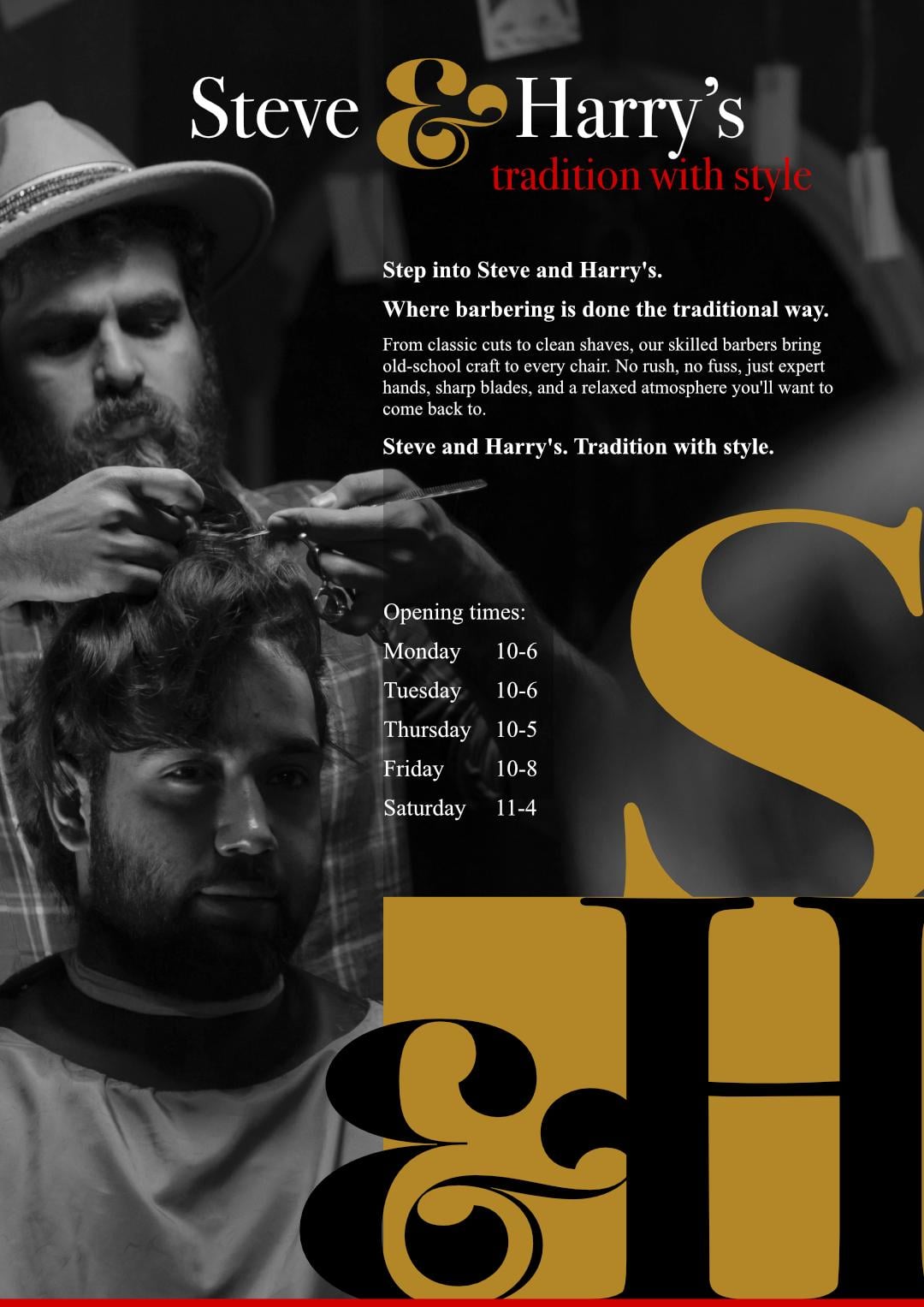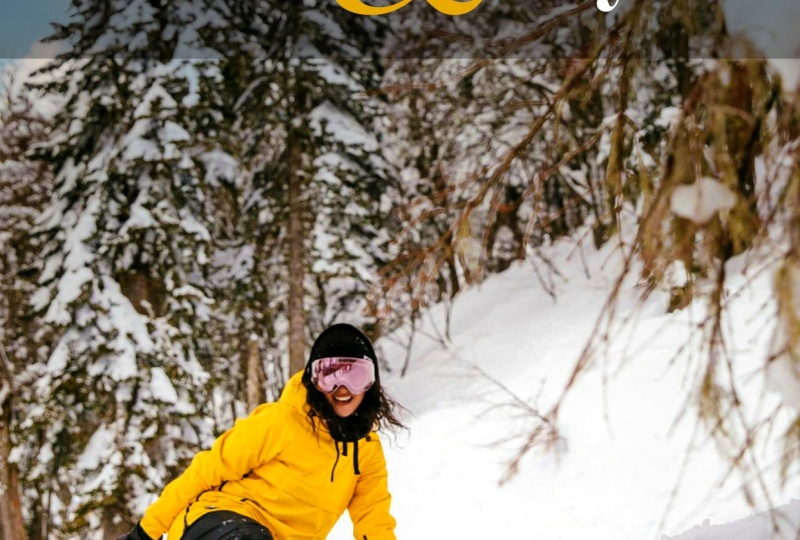
1. Diseño de texto: Introducción a este curso: El texto es una
parte tan importante de la vida cotidiana. En este curso, quiero
guiarte a través de cómo
crear
texto hermoso, asombroso y llamativo en Affinity. Este curso
te ayudará a dar vida
a tus ideas a través de
imágenes que informan, inspiran y expresan
tu visión única Empezaremos por
algunos de los conceptos básicos y trabajaremos nuestro
camino a través todos esos pequeños trozos de texto que probablemente
nunca antes habías notado. Estas son algunas de las
cosas increíbles que vas a hacer con el
texto. Echa un vistazo. Hola. Yo soy Tim. Vivo y trabajo en
¿A qué esperas? Comencemos ahora mismo, y
empecemos a crear juntos. Dos.
2. Propiedades de formato de texto: introducción: En esta sección,
vamos a estar viendo las
propiedades del texto. Entonces podría ser alejar más a tus
personajes,
alejar más las líneas, los párrafos más
separados, sangría, todo ese tipo de cosas
que necesitas saber para realmente bueno de aspecto
profesional. Empecemos.
3. Trabajar con rompes de cuadro y columna: Echemos un vistazo a trabajar con el texto dentro de los marcos. Ahora bien, lo que quiero hacer es que este pedacito de texto
fluya de este fotograma a otro aquí abajo. Y sí,
esto lo hemos hecho en el pasado. Pero lo que voy a
hacer es simplemente mostrarte nuevo muy rápido por
si te has olvidado. Tomas tu marco,
vas por aquí, y lo que estamos
buscando es una pequeña flecha. Ahí está por allá.
La pequeña flecha roja, y puedo hacer clic en
esa flecha roja, y luego puedo hacer clic en
arrastrar por aquí, y el texto fluirá de
un fotograma a otro. Además, si queremos dividir los marcos en dos
o más columnas, voy a dar click en el marco, y puedo subir aquí
para dividirlo. O también podemos hacerlo
yendo al menú Ventana, bajando al texto y encontrando el panel del marco de
texto. Y en el panel del marco de texto, podemos hacer lo mismo
y podemos
dividirlo en diferentes columnas y cambiar la cuneta
ahí también Ahora, lo que quiero hacer es mirar cómo podemos trabajar con
el texto en esos marcos. Se puede ver que tengo algo de
texto en diferentes marcos. Todos están enlazados de uno a otro, no
a la página siguiente. Y también tengo aquí, tengo algunos encabezamientos para
las distintas secciones Entonces si hacemos zoom por aquí, pueden
ver que tengo la imagen como
documento de existencia. Ese es el primer párrafo. Entonces prueba tangible de presencia es el siguiente
párrafo de aquí. El elemento humano
de la imperfección, ese es este grano es
tan impredecible, es ese, y la filosofía de intención es la última aquí dentro Ahora bien, esto está bien, pero se ve desordenado porque
tenemos el rumbo para allá, y listos queremos
que esté aquí abajo Ahora bien, una de las formas en
que podemos hacer esto, comencemos con esta
de aquí es si tuviera que hacer clic ahí
y poner una devolución, puedo obligarla a pasar
a la siguiente columna. Y lo mismo por aquí.
Voy a ir a allí, y voy a hacer unas cuantas devoluciones para forzar eso ahí.
Lo mismo con este. Y vamos a mover esa de otro lado. Y con bastante
gusto puedes hacer esto. Para conseguir que todo vaya
a las áreas apropiadas. Y ya ves que
prácticamente lo he hecho ahora. Pero acabando de hacer eso, me he dado cuenta de que
me he olvidado de tomar la prueba tangible de
presencia y moverla hacia abajo. Entonces hagámoslo ahora mismo. Entonces regresa ahí,
lo mueve hacia abajo. Y luego, por supuesto,
eso estropeó este, que tipo de puede
estropearlo, se puede ver cómo hay un poco de brecha y hay
una brecha ahí, y hay un poco de brecha en la parte superior de esa, también Entonces sí, puedes hacerlo de esta manera, pero no es lo ideal. Voy a deshacer esto
e ir todo el camino regreso allá vamos. De vuelta a donde
estábamos. Entonces, en cambio, lo que podemos hacer es en realidad
podemos obligar al
texto a pasar de un
fotograma a otro. Echemos un vistazo a
este de aquí. Entonces he puesto mi cursor justo delante de la prueba
tangible de presencia, y voy a ir al texto, y estoy buscando
algo que me
permita empujar el texto
al siguiente fotograma. Y eso es aquí abajo.
Tenemos inserto. Quiero insertar
algo que va
a empujar el texto, y
eso va a ser un descanso. Y voy a
elegir una rotura de marco, así que va a romperse y empujar eso de ahí a ese. Ahora, eso se ve bastante
bien allá porque esa está perfectamente alineada.
Pero vamos al grano. Y una vez más, el grano, voy a empujar
también, así que voy a volver de nuevo al texto. Abajo para insertar roturas, y voy a hacer una
rotura de marco en esa también, que lo empuja aquí adentro. Siguiente, igual otra vez. Vamos a ir por aquí, ir al texto, insertar descansos. Rotura de marco. Pero ahora
mira lo que pasa. Con la rotura de marco, dice, vaya al siguiente fotograma. No pasa a
la siguiente columna. Entonces apuesto a que en realidad ya puedes ver lo
que voy a hacer. Voy a regresar y hacer
eso otra vez, pero esta vez, voy a pasar
de texto, insertar,
saltos, voy a
usar un salto de columna, lo que te obligará a
pasar a la siguiente columna. Así que de nuevo por aquí, entonces
puedo usar lo mismo. En este caso, ya sea rotura de
columna o marco. Así que vamos por allá descansos. Haremos que ese
pase al siguiente fotograma. Allá, y ahora todo eso está
funcionando perfectamente. Entonces, si tengo un problema aquí y decido
hacer algunos cambios, no importará
porque estos
siempre saltarán a los lugares
apropiados. En fin, he incluido este pequeño documento para
que lo pruebes. No he vuelto
a donde era un problema. Prueba esto o
prueba el tuyo también.
4. Opciones de texto fuente, familia de fuentes, tipos de letra y contornos: Ahora, voy a ir a
buscar mi Panel de Personajes, y obviamente, tal vez lo
encuentres aquí arriba. De hecho puedo ver el mío ahí. El CH acababa de mostrarse. Pero si no puedes, ya sabes
dónde encontrarlo, menú Ventana, abajo al texto y los caracteres obviamente ahí dentro.
Vamos a sacar eso. Ahora, echemos un vistazo a
algunas de las opciones aquí dentro. Ahora bien, si has hecho el lado
vectorial de Affinity, sabrás bastantes
de estos bits y piezas, pero tengan paciencia conmigo, puede
que haya algunos bits extra que
recogerás esta vez, también. Ahora, lo primero son
las fuentes de aquí. Se puede ver esto dice A fuentes, y puedo elegir entre
diferentes subconjuntos de fuentes Así que podría ir a
mis fuentes en inglés o mis fuentes favoritas en sus fuentes recientes que
he estado usando fuentes divertidas. La lista simplemente continúa.
Voy a elegir todas las fuentes así que
las pongo todas ahí. Voy a seleccionar algunos textos. Voy a ir a este
pedacito de texto por aquí. Vamos a acercarnos un poco
a ese bit de texto. Solo usando mis atajos, Control Comando más
para acercar un poco, y voy a seleccionar
ese trozo de texto ahí haciendo clic algunas veces
con mi herramienta Texto. Entonces tenemos la
primera fuente por aquí, que en mi caso,
dice Aéreo. Ahora, cuando te encuentras con fuentes, a veces
encontrarás que en realidad se las conoce como fuentes. A veces pueden
denominarse tipos de
letra, a veces familias de
fuentes Entonces, ¿cuál es la diferencia? Bueno, si voy a
Aéreo por allá, aéreo regular 12 puntos
por ahí hay una fuente. Mientras que just aerial por
sí mismo es la familia de fuentes. La familia de fuentes incluye
regular, incluye cursiva, incluye negrita,
negrita cursiva y todos los diferentes tamaños. Solo teniendo en cuenta cuando la
gente habla de fuentes, lo
usan como término genérico realmente para incluir
las familias de fuentes. Es exactamente lo
mismo con los tipos de letra. letra son como
familias de fuentes donde se puede ir a aéreo y eso incluye todos
los diferentes estilos
y tamaños. Si solo quieres
llamarlos fuentes, bueno, solo las personas más tensas
se entusiasmarán con eso De todas formas, me voy a mudar
un poco hacia abajo por aquí. Voy a ir
al tamaño porque cuando tienes un poco de texto y tienes
el tamaño ahí, el tamaño viene en puntos. Ahora bien, en lo que respecta
a los puntos, ¿qué tan grandes son los puntos? Bueno, en una computadora, hay 72 puntos en una pulgada. Entonces, si seleccioné este título por aquí y pongo
72 puntos ahí dentro, solo
vamos a ir a 72. Ese sería 1 "
texto alto en mi documento. Pero, ¿y si no te
gusta usar puntos ahí dentro? Y pensaste,
Bueno, ¿sabes qué? Realmente quiero que ese pedacito de texto sea exactamente de
8 milímetros. Bueno, puedes
teclearlo directamente, así puedo entrar aquí y
puedo escribir ocho MM, presionar Enter, y
lo convertirá en tamaños de puntos
para mí, también. Sólo un poco
de un lado aquí, sí
dije que hay
72 puntos en una computadora, y eso es porque la
tipografía tradicional , en realidad es 72.27 Así que por si acaso
alguien te detenga y te diga:
Bueno, en realidad, hay 72.27 Ya sabes de lo que están
hablando. Eso es tradicional. Estaba
en una computadora apenas 72. Ahora, bajemos un
poco por aquí, y tenemos los botones
habituales que ves en todo
tipo de cosas. Entonces por aquí,
tenemos subrayado. Tenemos por aquí, subrayados
dobles ahí dentro Tienes pasos de strike throughs y tienes doble
strike throughs, y luego puedes
eliminarlos ahí dentro. También puedes, si lo deseas, entrar aquí y cambiar el color, así podría hacer un subrayado
rojo
allá con este pequeño
color de aquí Voy a simplemente
deshacerme del subrayado dando clic de nuevo en la U del
lado izquierdo Ahora bien, ¿qué es este de
aquí abajo que dice ninguno? Bueno, voy a seleccionar
este pedacito de texto por aquí. Podría hacerlo un
poco más grande. Entonces 22 puntos, creo que voy
a ir 30 puntos ahí, solo para que sea más fácil que
veas . Voy a ir por aquí. Haga clic en eso, elija un color. Vamos con algo
bastante brillante y vibrante y aumentemos el tamaño y verás
exactamente lo que hace. Es la línea alrededor del
exterior del texto. Podría hacer eso y
poner la línea alrededor la parte exterior del
texto ahí dentro,
y entonces en realidad podría
quitar el centro de mi texto. Puedo ir al
color de mi texto y luego decir ninguno, y eso solo dejará
texto abierto con solo el contorno. Verás si lo muevo y vamos a pasarlo por encima de la foto. Voy a
traerlo al frente, así que voy a subir
por aquí a mis capas, y voy a ir
a rango y decir,
llevar al frente, y se
puede ver cómo ese texto es realmente
transparente en el medio. Así que sólo voy
a deshacer eso para que
lo veas otra vez por allá. Entonces, si tienes algún texto, puedes ponerle una línea alrededor. Vamos a ir a las decoraciones
de aquí una vez más, y entonces puedo elegir
un color ahí dentro. Y luego puedo ir a la talla, y puedo cambiar el tamaño en eso para la línea
alrededor del exterior. Si quiero deshacerme del color de
relleno del texto, puedes subir aquí, el
segundo a lo largo, así que es, perdón, el primero
largo, alguien a la izquierda. Cambia el color de la fuente a ninguno.
Esa es una pequeña línea roja. Y ahora eso está bien, texto
invisible, pero la línea alrededor del exterior es visible. Voy a volver
otra vez por aquí al tamaño de eso, y pueden ver cómo puedo ajustar el tamaño con el texto
invisible ahí dentro. También puedo ir y usar
cualquiera de estos otros estilos, así podría ir y tenerlo como
una línea punteada por allá. Ahora bien, la otra cosa que podemos
hacer es que podemos alinear esa línea, y podemos
optar por tenerla en la
propia línea por dentro
o por fuera. Tú eliges cuál prefieres. Vaya un poco con eso y particularmente con
las decoraciones, si nunca ha probado estas
líneas alrededor del exterior
del texto o texto transparente
con la línea. Tener una oportunidad.
5. Posición y transformación del personaje: Yo vayamos a posicionar
y transformarme. Si no puedes ver estas opciones, simplemente haz clic en la pequeña flecha de
ahí para abrirla. Ahora bien, el primero al
que llegamos aquí es algo
llamado kerning cambia las
distancias entre caracteres
individuales.
Déjame mostrarte. Voy a ir por aquí
y voy a acercarme un poco por allá a la IA,
donde dice IA generativa, y voy a hacer click para que mi herramienta de texto esté sentada
entre la A y la I. Ahora lo que puedo hacer es que pueda ir junto a mi kerning
y puedo o bien aumentar esa distancia que
ves toma un poco Hay
ajustes muy, muy finos por allá, o podría disminuir
esa distancia ahí dentro. Pasemos a una
cifra menos para que podamos empujarlo muy
cerca si es necesario. Ahora bien, para la mayoría de los textos, no
necesitas
cambiar
mucho el enlatado a menos que estés tratando de
hacer algún tipo de efecto Pero si descargas
alguna fuente interesante, que tal vez no esté tan bien creada en primer
lugar o bien diseñada, encuentres que el timón
no se ve bien y es posible que tengas que
entrar y
curarlo manualmente tú mismo Muchos diseñadores pasan horas
y horas simplemente ordenando la conning en su texto
para que sea así Y es bastante divertido
una vez que te metes en ello. Pero si solo quieres
poner algún texto muy rápido y tienes
un tipo de letra bien diseñado, como Ariel, por ejemplo, no
necesitas hacerlo
cono a menos que
quieras hacer un efecto específico Ahora, sigamos adelante. Si voy aquí abajo a
este VNA por aquí. Ahora, para este VNA, necesitamos seleccionar las palabras Seleccionaré la palabra
en lugar de
simplemente poner el cursor
entre los dos caracteres. Y por aquí, puedo aumentar las distancias entre esos
personajes o disminuirlos. Ya ves que puedo ir a negativo o puedo ir positivo allá. Y voy a dar
click en ese
desplegable y volver a cero. Ahora bien, ten cuidado con
este porque si lo
pones en un texto normal como este, podrías terminar
siendo tu texto bastante difícil de leer si está demasiado separado o
demasiado cerca. Un poquito de
esto puede ayudar si, por ejemplo,
quieres empujar un trozo
de texto a la siguiente línea, o si solo tienes una palabra sentada
sola y quieres que esa palabra
vuelva al resto
del párrafo, tal vez
quieras seleccionar todo
el párrafo y ajustarlo
muy, muy ligeramente. Pero no te vayas
por encima con eso. Ahora bien, hay
momentos en los que quizás quieras
poner mucho kerning, pero eso volvería a
ser para más efecto Entonces digamos, por ejemplo, con este bit por aquí,
solo quiero la palabra existencia. Entonces voy a quitar este
pedacito de texto por ahí. Yo sólo voy a poner una E ahí. Y me gustaría hacer esto más cinematográfico así que
es más importante Voy a bajar por
aquí y voy a aumentar eso para conseguir más
distancias entre ellos. Así que eso le da una
sensación más cinematográfica. Encontrarás que la
gente suele usar esto cuando se trata de encabezados. Tu texto grande se ve muy, realmente cinematográfico, se ve
muy, muy bien así Pero para el texto corporal normal, no lo
usaría a menos que esté buscando mover algo
de una línea a la siguiente. Echemos un vistazo a ajustar las distancias
entre las líneas. Esto se conoce como líder. Entonces, si voy aquí abajo, verás que
puedo o aumentar las distancias o
disminuir las distancias. Si no estás seguro de lo que debes usar, simplemente haz clic en esto. Se despliega y elige auto. Y ese será
el líder normal para ese trozo de
texto en particular o esa fuente en particular. Ahora, tenemos algunas
otras opciones aquí. Por ejemplo,
puedes tomar tu texto, y puedes obligarlo
a que se ponga todo en cursiva. Puedes moverte hacia abajo, y puedes cambiar el tamaño del texto y
hacerlo tan ancho Puedes hacerlo alto. También. Y por último, aquí abajo, entonces
podemos entrar y podemos usar superíndice o subíndice, y eso va a tomar algo
y hacerlo pequeño y subir Entonces, por ejemplo, después de la
palabra fotografía aquí, tengo TM marca registrada, y puedo seleccionar eso y luego
puedo ir y hacer
ese superíndice, que lo hace un
poco así Si uso subíndice, hará
lo contrario y lo
hará pequeño y bajará Elige ninguno para
volver a tu original. Tener un poco de un ir con eso. Y en el siguiente video, lo
estoy llamando por la
madriguera del conejo porque voy a entrar en muchos más
detalles aquí. No necesitas todos los detalles. Si quieres saltarte
eso y pasar
al siguiente video,
eso está absolutamente bien. Pero si realmente te
interesa más tipografía, entonces mira la siguiente
6. Al fondo de la aguja de conejo: posición y transformación: Entonces comencemos a
bajar por la madriguera del conejo.
Agárrate a un sombrero. Lo que voy a hacer
es echar un vistazo a algunas más de las
opciones que
no son tan normales como las habituales a las
que uno está acostumbrado. Entonces comencemos con este de aquí llamado
el cambio de línea de base. Verás, tu texto se asienta
sobre una línea de base invisible. Y lo que podemos hacer es ir a
lo largo del texto y
podemos seleccionar caracteres, palabras, o párrafos enteros. Y podemos cambiarlos, así puedo moverlos hacia arriba
o puedo moverlos hacia abajo. Ahora bien, ¿por qué
querrías hacer esto? Bueno, digamos que teníamos
algo así como una fracción. Ahora, voy a hacer
una fracción de 1/34. Así podría tomar el uno, y podría hacerlo subíndice, y podría tomar el 34 No, lo siento, superíndice. Y puedo tomar el 34, y puedo hacerlo
subíndice por allá Pero se puede ver que el
34 es demasiado bajo, así que puedo subir aquí
y puedo simplemente
empujarlo hacia arriba usando el
cambio de línea de base ahí dentro. También se puede utilizar
para todo tipo de efectos para texto así como para
poder moverlo. Ahora,
aquí hay una pequeña opción llamada no break. Si voy y decido que estas ciertas palabras
que quiero
mantener juntas como demasiado limpias, por
ejemplo, no quiero que sea división de palabras y una esté en una línea y una
en la Lo que puedo hacer es no ponerme descanso. Pero antes de hacer eso,
déjame
mostrarte lo que pasaría por aquí. Si empujo esto
más cerca, ahí vamos. Se puede ver que
tenemos dos limpios en dos líneas ahí dentro. Ahora,
déjeme hacerlo otra vez. Voy a seleccionar dos y limpiar, y voy a poner en
un no break por allá. Ahora, intentemos eso otra vez. Empuja esto demasiado limpio, y ahí vamos. Se puede ver que es simplemente empujado
demasiado limpio en la nueva línea. No ha puesto dos en uno
y limpio en el otro. Así que ningún descanso solo
te impide dividir palabras. Una vez más, pruébalo un
poco con eso, pruébalo. Esa es útil, pero el cambio de línea de base
es muy, muy útil.
7. Por el abismo del conejo: lenguaje, alineación óptica, puntuación colgante: Voy a ir
al idioma y
abrirlo muy rápido
porque aquí dentro, tenemos el idioma
para la ortografía, y no es solo el inglés. Se puede ver que hay variaciones
del inglés ahí dentro, y la otra que me parece bastante importante es la sílabe,
donde vas
a tener la sigrafía
automáticamente encendida
o ninguna automáticamente encendida
o Cerremos ese y
pasemos a la alineación óptica. Ahora, cuando eliges la alineación
óptica, obtienes esta pequeña mesa
de cosas realmente
rara aquí abajo. Entonces déjame mostrarte
cómo funciona esto. Lo que voy a hacer es que
sólo voy a volver a mi último texto aquí arriba. Y como pueden ver, aquí hay algunas cosas como
la palabra alucinar Y el alucinato tiene comas
invertidas alrededor de él. Así que voy a echar un vistazo
aquí al tipo que va a ser de tipo de
letra en lugar de ninguno. Voy a ir
aquí a los personajes, y se puede ver así es como controla a los diferentes
personajes y
lo que hace desde el movimiento de la izquierda y la derecha para
ciertos personajes. Aquí hay todo tipo de
diferentes. Voy a desplazarme un poco hacia abajo. Pero sólo vamos a
mirar las comas invertidas, y luego puedes como que descubras
cómo funciona
el resto de ellas tú mismo Déjame comenzar con alucinar. Y si hago un retorno por aquí, he puesto mi cursor antes las comas invertidas y
he hecho una devolución, puede ver que las dos comas
invertidas están
sentadas afuera, así que el texto está
alineado perfectamente Y eso es porque aquí
en la alineación óptica, tenemos el
encendido para esos personajes. Si solo elijo ninguno ahí, solo selecciónelo de nuevo y
elija ninguno por ahí. Se puede ver que simplemente vuelve
dentro del propio cuadro de texto. Puedes decidir lo
que quieres hacer. Voy a seleccionar eso
otra vez y por aquí, voy a elegir fuente y la
va a empujar afuera. Ahora bien, aquí es donde
puedes controlarlo tú mismo. Puedes entrar entonces puedes decir,
Bueno, en realidad, ¿sabes qué? En realidad quiero aumentar
eso un poco, así que sale justo ahí afuera
o disminuirlo un poco. Entonces puedes hacerlo
con la alineación
izquierda o derecha. Entonces como dije antes, ahí abajo
tenemos todo tipo
de opciones para
los personajes. Si no estás seguro de lo
que quieres, solo tienes que ir a ninguno ahí dentro
volverá al texto normal. Entonces, echa un vistazo
al lenguaje y a las
alineaciones ópticas que hay ahí dentro. Estoy tratando de no caer demasiado por la
madriguera del conejo con esto. Puedes meterlo más
en esos si lo deseas, pero solo quiero
darte un
bosquejo de cómo funcionan.
8. En el abismo del conejo: ligaduras tipográficas: Ahora, bajo tipografía,
una vez más, si no la puedes ver, da
clic en la pequeña
flecha que hay por Tenemos a este
pequeño FI aquí. Esto se llama ligadura. Ahora, las ligaduras, verás van a funcionar
a veces y no a otras. Entonces quiero mostrarles
qué es, qué hace, y por qué aparece y
a veces no ve, tengo un trozo
de texto por aquí, y este texto es aéreo. Y si enciendo y apago la
ligadura, puedes ver que todo lo que está
haciendo es
mover ligeramente la F y la
I más juntas Así. Pero donde las
ligaduras realmente se hacen propias es cuando
estás usando un tipo de letra, que tiene serifs, esos son los pequeños
rizos en los extremos Entonces, por ejemplo, si bajé aquí y elegí
algo con serifs, echemos un
vistazo y veamos si podemos encontrar algo aquí abajo Sólo voy a
correr todo el camino hacia abajo y encontrar Times New Roman, porque ese es un tipo de letra
serf muy tradicional Así que los tiempos New Roman por allá. Entonces, apaguemos las ligaduras. Y lo que encuentras
es que la F y la I sin ligaduras
están muy juntas Y tienes el
punto en la I y
el poco rizado en la F. Entonces lo que
hace una liicatura es que toma esos dos personajes y
los convierte en uno así Entonces sigue siendo legible como FI, pero se ve mucho mejor. También significa que si
estás haciendo impresión, a veces si no tienes
una liicatura así, estando
esos dos juntos, la tinta puede
correr entre ellos y crear una gran
gota de tinta ahí dentro, que se ve muy
pobre desde Entonces eso es todo lo que hacen las liicaturas. Toma ciertos
personajes y los
convierte en un solo personaje que en
realidad sigue siendo dos
personajes así. Pruébalo con
diferentes tipos de caras, y verás las diferencias. Como dije, realmente solo funciona correctamente en aquellos que tienen un poco rizado en
la parte superior, las serifs Al mirar algunas más de
estas opciones por aquí, tenemos todas las capitales. Ahí tenemos
capitales pequeños. Entonces, si la F, por ejemplo, en Find era una mayúscula
y yo lo hice,
verás que tendría
un gran capital y luego las
capitales más pequeñas ahí abajo Estos dos de aquí son
superíndice y subíndice, y este te permite
convertir las cosas en fracciones Ahora bien, esto
depende de la fuente que realmente
estés usando. Voy a ir a buscar
un poco de texto aquí. Este texto es aéreo y
voy a ir a poner aquí una fracción. Voy a hacer una barra cuatro. Voy a seleccionarlo y
luego presionar ese pequeño botón y lo convertirá en una fracción de aspecto
agradable para mí. Déjame deshacer eso.
Pero si hice uno, sé, 32, una vez más, selecciona eso
y da click en eso. No tiene un solo
carácter para reemplazar eso, así que tienes que hacer
algunos de esos manualmente. De igual manera, cosas como S T
y así primero, segundo, ND, RD para tercero, si tu
fuente lo soporta, puedes reemplazarlos muy rápidamente con esos
pequeños botones ahí dentro. De lo contrario, todo lo que
necesitas hacer es seleccionar los caracteres
que quieras y usar
superíndice y subíndice y
luego tal vez moverlos hacia arriba y hacia abajo usando el
cambio de línea de base para que las cosas Tengan un poco
de oportunidad con eso, particularmente entendiendo
cuáles son las ligaduras, y luego saldremos de la madriguera
del conejo
9. Opciones de párrafos: alineación: Et, echa un vistazo a
las opciones de párrafo. Ahora, pongo algo de texto en
otra página aquí solo para que sea fácil para ti verlo sin todas las distracciones,
fotos, etcétera Y voy a ir a
buscar mi panel de párrafos. Voy a cerrar el panel de
personajes. Ahora, obviamente,
si no lo encuentras, ya
sabes a dónde ir,
menú de ventana, texto, etcétera Entonces, antes que nada, las pequeñas
opciones a lo largo de la parte superior. Ahora, sé que estos parecen obvios, pero hay una o dos cosas
que quiero mencionar. Solo seleccionemos
todo este texto, y tengo la
línea izquierda o la línea central, línea
derecha por ahí. Ahora tienen perfecto sentido. Estos siguientes de aquí, aquí es donde se alinea a
ambos lados del marco de texto, pero la última línea está
alineada a la izquierda Esa de ahí, la
última línea está alineada a la derecha y
esta a la pena, a la mitad y esta
a la derecha. Pero se puede ver porque es que los titulares son solo
una línea por sí mismos, los alinea también Entonces, si quisieras usar esos, me aseguraría de que
no lo hiciste en el titular. Por supuesto, esto es
algo que puedes configurar y veremos más adelante con estilos. Así que allá,
solo podría hacer uno de esos. Ahí. Ahora, esos son esos tres. Este de aquí se
trata de conseguir que
el texto se siente en todas las líneas y
llene todas las líneas, lo que podría verse muy
bien desde la distancia. Pero se puede ver lo que
se hace con esta última línea es que simplemente se ha separado
las palabras, y hace que parezca
bastante ilegible, todo si lo haces sobre
todo así Mira lo horrible que
se ve en este momento. Es decir, esta de aquí se
basa en una reacción fotoquímica. Incluso en el párrafo, se
ve muy, muy mal. Pero, ya sabes, si
quieres, ve a por ello. Ahora, vamos a echar un vistazo a éste de aquí o a
estos dos, ¿diría? Porque esto es
ligeramente diferente. Se puede ver que tenemos una línea a la izquierda y una línea
a la derecha ahí. Pero estos tienen el mismo aspecto. Esa parece la
línea a la derecha. A lo largo de entonces, si hago clic en él. Bueno, funciona exactamente
igual que este de ahí dentro. Entonces, ¿cuál es la diferencia
entre estos dos? Bueno, tiene que ver con tener
un pliego de página doble. Si tienes una doble
página extendida como esta, si voy a esta opción de escritura
alineada, puedo mover esto, solo vamos obtener la herramienta de movimiento y
moverla a través de este sitio, y sigue siendo
escritura alineada. Pero digamos que siempre
quise que mi texto estuviera alineado
al centro de la página. Bueno, si elijo este de
aquí, vamos una vez más, sólo
vamos a ir y
seleccionar todo el texto, y voy a elegir
este de aquí, que dice alineado
hacia la columna vertebral. Ahora mira lo que pasa. Si tomo este pedacito de texto y lo
pongo de ese lado, entonces
se alinea de la manera opuesta Por lo que automáticamente simplemente salta y
se alinea con la columna vertebral Entonces tenemos este
de aquí, que se alinea
lejos de la columna vertebral Entonces, una vez más, puedes
ver cómo se mueve eso, dependiendo de si
estás en una página del lado izquierdo o derecho. En fin, ¿tienes un
poco de juego con esos? Es interesante
saber de esos. Podrías o quizás
no los necesites nunca, pero es bueno
saberlo. Pruébalos.
10. Espacio de párrafos e indentación: Echemos un vistazo a algunos
de estos los importantes. Entonces, antes que nada, iniciando aquí arriba, podemos sangrar. Entonces voy a ir
a lo largo de este párrafo aquí y puedo sangrarlo
desde el lado izquierdo, y también puedo sangrarlo
desde el lado derecho Voy a ir al siguiente
párrafo, éste de aquí. Sólo lo estoy resaltando, y debajo de eso en el lado
izquierdo aquí, podemos sangrar la
primera línea si queremos Eso es bastante útil.
Si vas a estar haciendo en lugar de hacer espacios
normales entre
tus párrafos, solo
puedes usar esto para
denotar un nuevo párrafo Ahora, echemos un
vistazo a estos dos de aquí, donde tenemos espacio
antes y espacio después. Ahora bien, lo que voy a hacer
aquí es que voy a seleccionar este pedacito de
texto por allá, seleccionar todo para
que lo veas fácilmente entre ese encabezado
y ese rumbo de ahí. Entonces puedo seguir adelante y puedo aumentar el espacio después de eso. Ahora, también puedo aumentar el
espacio antes de allá. Podrías, por cierto,
si se pone a cero, quizás
tengas que
ir un poco primero antes de que realmente
empiece a moverlo. Así. Por lo que estos dos permiten más espacio antes o
después de los párrafos. Por cierto, si se trataba dos párrafos en ella funciona también
entre párrafos, no
se trata sólo de entre titulares y el otro y
los propios párrafos. Como pueden ver, sólo puedo
mover esos alrededor así. Entonces, una vez más, prueba aquí las opciones
importantes, que es la alineación por ahí o la sangría, ¿debo Y luego también, esto
es muy importante, el espaciamiento entre
los párrafos.
11. Control de la pestaña de párrafos: Tengo algunas pestañas aquí. Así que lo que he hecho es que
he pulsado la tecla de tabulación y he puesto un
número ahí dentro, luego tabulación de nuevo otro número, número tabulación número de tabulación. Y voy a seleccionar a
los de aquí. Y vamos a bajar
a las paradas de tabulación. Ahora bien, si no los puedes ver, es simplemente hacer clic en el pequeño
menú desplegable que hay por ahí. Y se puede ver con las pestañas, en realidad
puedo cambiar las distancias de esas pestañas y moverlas así. De hecho, podemos ir un poco
más allá y hacer clic en el más, y luego tenemos más
control sobre la pestaña. Entonces aquí tienes
cosas como alineación. Y solo hay
tantas opciones más. Si haces clic en esos tres
puntitos ahí dentro, puedes ver las alineaciones,
puedes ver el líder Eso es lo que pasa
en el mismo frente. Entonces, por ejemplo, si hice
clic en el guion bajo, verás que tenemos al
líder justo por ahí Y luego una vez más,
la posición, que es la de ahí dentro. Ahora, sólo voy
a cerrar eso abajo porque entonces si quiero
ir y agregar algo de moin, solo
voy a hacer una tabulación y luego poner otro número Y una vez más, una ficha y luego
otro número por allá. Y es usar esos tabuladores ahí dentro, esos 20 milímetros. Pero siempre puedes
cambiarlo. Puedes seleccionar eso, y puedes entrar
y puedes ajustar las distancias de pestaña ahí dentro. Echemos un vistazo a otra
forma de trabajar con pestañas. Voy a usar mi herramienta Texto
y voy a dar click en esta pequeña área de costos de química donde ya hemos hecho
las pestañas. Y voy a
subir al
menú Ver abajo para mostrar y
voy a mostrar la regla de texto. Ahora, en la regla de texto, puedo ir y
sólo puedo poner una pestaña en alguna parte. Entonces todo lo que tengo que hacer es
hacer clic ahí y
se puede ver una pestaña que ha
aparecido ahí dentro. Y puedo mover esa pequeña pestaña hacia atrás y hacia adelante
independientemente. Déjame ir por aquí
y hacer clic de nuevo. Y una vez más, ese
se puede
mover por donde quiera ir. Haré clic en
otro por aquí, y eso será para
éste. Y lo mismo otra vez. Así que en realidad puedo
medirlos exactamente en esta regla y simplemente poner pequeñas pestañas ahí
y moverlas. Si quieres
deshacerte de ellos,
simplemente puedes hacer clic y arrastrar hacia arriba para eliminar esas pequeñas pestañas
de la propia regla de tabulación. Pruébalo.
12. El abajo del conejo: viudas y huérfanos: Ahora, bajemos un poco por la
madriguera del conejo aquí. Y en realidad, esto es algo
que es bastante importante. Y es posible que se escuche en voz alta que la gente
habla de viudas y huérfanos No es necesariamente
solo afinidad, es publicar en general. Entonces echemos un vistazo
a las viudas y a los huérfanos. Tengo algo de texto por aquí, y tenemos este pedacito de texto, esos dos párrafos, y luego fluye de
aquí a ese marco de texto. Ahora bien, esto podría estar
en una página diferente o podría estar en la misma página. No hace ninguna diferencia. Y ahí voy a seleccionar
todo ese texto. Y vamos a ir a
las opciones de flujo por aquí. Ahora bien, ¿qué es una viuda? Bueno, por aquí,
verás que este párrafo dice fotografía digital por su naturaleza, bla, bla, bla,
bla, bla, película analógica, sin embargo, se basa en el proceso fotoquímico
o reacción
fotoquímica, se basa en el proceso fotoquímico
o reacción
fotoquímica o Entonces este es un párrafo
de ahí abajo para allá. Ahí está el siguiente
párrafo por aquí. Y esta pequeña línea de aquí, porque está sentada por
sí sola se le conoce como viuda. Entonces, ¿qué podemos hacer? Bueno, en realidad podemos aquí abajo, podemos evitar
viudos últimas líneas Entonces, si hay una línea como esa, simplemente
hacemos clic en prevenir
viudos última línea, y obliga a esta línea aquí a ir y unir
esa línea ahí Entonces no tienes estas líneas
al final sentadas solas. Ahora, huérfano, por otro lado, por aquí, vamos y echemos un poco de un vistazo a esto Entonces tengo este poco de texto. Aquí, voy a
seleccionar todo el texto, así que fluye de ahí
a esa página de aquí. Y esta vez, tenemos el inicio del
párrafo aquí arriba, solo la una línea de párrafo
antes de que el párrafo
continúe ahí dentro. Entonces este es un huérfano. Vamos y vamos a decir
prevenir huérfanos primeras líneas. Entonces damos click en eso y se
puede ver cómo obliga ese párrafo a ir y unirse
al resto del
párrafo ahí dentro. Por supuesto, ha dejado
el título por ahí, y eso es algo que hay
que mirar por separado. Pero sí significa que
si está en medio de muchos textos con párrafos
diferentes, no solo tendrás una
línea sentada sola. En fin, una vez más
, pruébalo. He incluido todas las opciones en este documento en particular
para que puedas probar un poco con
esas tú mismo.
13. Por el abismo del conejo: balas: Ahora, probablemente hayas
visto o podrías haber usado los dos botonitos
en la parte superior para las viñetas. Entonces voy a seleccionar el texto. Y como pueden ver,
puedo activar y desactivar
las viñetas .
Déjame deshacer eso. Y puedo hacer lo
mismo con la numeración y apagarlo, también. Pero ¿y si
quieres profundizar? Y, antes que nada,
si has
encendido balas y las vuelves
a apagar, ¿por qué las cosas van raras? Entonces bajemos por las
balas madriguera del conejo. Voy a deshacer eso. Y volvamos al texto original. Entonces voy a seleccionar este pedacito de texto que
quiero convertir en balas. Y cuando enciendo
balas aquí, lo que notarán en mis opciones de
párrafo es, si bajo y encuentro balas
y numeración por allá, entonces
tengo el tipo
que es balas aquí adentro. Así que tengo un tabulador
para poder
controlar a dónde van esas balas. Y la primera línea, debo decir, puedo controlar eso ahí dentro. Pero, ¿qué pasa con el
resto del texto? ¿Cómo puedo controlar eso? Bueno, si recuerdas, y vamos directo a la parte superior
por aquí, nuestro sangría, podemos controlar el resto del texto con
la
sangría Entonces, si llegas
al grano y
lo apagas y te vas, Oh, Dios mío, ¿
qué pasó aquí? Podemos gritos. Simplemente podemos seleccionar ese bit de
texto por ahí. Y ahí dentro podemos
bajar esto a cero. Entonces nuestra sangría es en realidad también
parte de las balas. Hagámoslo de nuevo y
tomémoslo un poco más. Entonces, si hago clic por ahí,
voy a simplemente, creo, empujar eso
un poco así. Entonces he ido a 14 ahí. Voy a ir a mis balas
y voy a poner 14 ahí también,
así que todo se mueve a través. Y no me gustan estas plazas. Probablemente tienes puntos en el tuyo. Entonces, si vas a esta
cuadradita de aquí y hago clic ahí,
puedo deshacerme de eso. Y si voy al menú desplegable, puedo elegir otro
tipo de bala. Y voy a ir con esta forma de diamante vacía por
allá en su lugar. Secado.
14. Al abajo del conejo: numeración: He quitado mis balas, y quiero poner algunos puntos
numéricos aquí ahora. Entonces voy a seleccionar
esos párrafos, y puedo ir y simplemente
elegir mis números ahí dentro. Ahora, echemos un
vistazo a las balas y numeración aquí
abajo porque tenemos
diferentes tipos de numeración, así puedo ir ABCD, puedo ir uno, dos, tres, cuatro La lista es interminable en cuanto
a lo que puedes hacer. Pero tenemos
algo más aquí llamado niveles. Entonces, digamos, por ejemplo, que aquí tengo este
párrafo, y luego éste, voy a hacer una devolución. Entonces, en realidad, eso se ha ido a dos. Pero en serio, quiero que
esta sea la parte A del primer punto de viñeta. Entonces por aquí, si selecciono esto, si elijo ese
para que sea el nivel dos, puede ver que solo
dice uno de nuevo. Y ahora puedo cambiar eso a A. Y si entonces hago un retorno
por aquí, eso se convierte en B. Así que tenemos uno A y B, que están en el nivel
dos, y luego dos, tres y cuatro,
que son el nivel uno. También puede agregar diferentes niveles de números dentro de los conjuntos de números. Tengan un poco de juego con
eso y vean lo que pueden hacer. No lo olvides, tienes cosas como el tabulador ahí dentro y también la sangría izquierda para
jugar al mismo tiempo Entonces, ya sabes, podríamos
tomar algunos de estos y simplemente sangrarlos un
poco más, y simplemente
retrocederemos eso un poco
así y
lo cambiaremos retrocederemos eso un poco aquí también Diviértete con eso.
15. Calabaza letras: letras capitales, decoraciones, solapado y palabras iniciales: Et mira las últimas opciones
en este panel de párrafos. Oh, déjame alargar eso otra vez. Entonces cerraremos la numeración de
balas, y yo también voy a
cerrar el espaciado. Y bajemos por aquí.
Tenemos separación por sílabas. Entonces hay todo tipo de
opciones en la separación por sílabas. Si dices usar la
separación automática de palabras ahí dentro, puedes elegir, por ejemplo, la longitud de palabra que quieras Entonces, si el número de caracteres
es superior a una cierta longitud, se autoseparará por sílabas, o
no lo hará ahí dentro. Hay tantas opciones
para probar aquí. Y honestamente, si
las pasara por todas al final, creo que habría perdido a
todos porque
estarías profundamente dormida. Entonces vamos a
dejar esa. Si entras en la separación por sílabas, ten una obra de teatro, tiene sentido
una vez que te metes en Entonces tenemos gorras de caída. Ahora, mayúsculas, y voy a seleccionar este
párrafo por aquí que veas de lo que estoy
hablando es cuando tomas el primer personaje y lo haces más grande para que veas
que esto es tres líneas de alto por ahí. Pero podría hacer que sea
dos líneas de alto si
quisiera o cuatro líneas de alto. Así que solo puedes cambiar el
tamaño de ese primer personaje. Se usa bastante
en los libros de allá, y ahí podemos ajustar más
ajustes. Entonces tenemos palabras iniciales. Ahora, sólo me voy a
quitar los gorros de entrega. Y con palabras iniciales, entonces
podemos optar por aplicar
un estilo a la primera, por muchas palabras
en un párrafo. Entonces, si hago clic en Habilitado, puedes ver que dice el número
máximo de palabras tres. Ahora bien, ¿por qué no ha cambiado
nada? Bueno, por aquí,
voy a ir y voy
a cambiar el estilo. Entonces voy a decir,
quiero que esto sea fuerte, así que lo hará audaz. Y se puede ver que las
tres primeras palabras están en negrita ahí dentro, y entonces puedo elegir cuántos caracteres
quiero efectuar ahí dentro. Por último, saltemos
a las decoraciones. Las decoraciones permiten hacer pequeñas líneas o áreas
que están coloreadas. Entonces por aquí, voy a
hacer click en eso. Voy a decir, vamos a tener
una línea en el lado izquierdo y una línea en el
lado derecho por allá. Entonces, si tuviera que hacer
clic fuera de eso, se
puede ver allá. Tenemos esas pequeñas líneas, una en ese lado, y
otra en ese lado. Seleccionemos esto de nuevo. Uy. Intentemos eso de
nuevo, selecciónelo. Voy a apagar esos dos. Podría optar
por tener todo
el asunto coloreado, y ahí tenemos gris. Y luego aquí abajo,
puedes cambiar los colores. Se puede cambiar la transparencia. Voy a cambiar
eso a un azul pálido, creo, ahí dentro. Una vez más,
juega un poco con estos ajustes. No los vas a usar todos
los días, pero es importante saber dónde están para cuando
los necesites.
16. Navegador de Glyphs: Yo ahora tienes todos tus párrafos y tus opciones de personaje y
puedes controlar el texto. Pero, ¿y si
encuentras que necesitas un personaje específico,
y no lo puedes ver? Bueno, la forma de evitar esto es usar algo
llamado glifos Voy a ir al menú
de la ventana. Voy a bajar al texto, y voy a mostrar
el navegador de glifos Ahora, los glifos son todos los
caracteres de todos los conjuntos de fuentes. Entonces por el momento, estoy en aéreo, y estos son todos los
diferentes personajes que en realidad están en aéreo. Se puede ver
que hay tantos de ellos. Voy a parar por ahí. Ahora bien, si necesito
usar un personaje,
entonces por ejemplo, en este caso, podría querer usar una marca de
registro porque tal vez una prueba
tangible ha sido autor o ha
sido Entonces lo que hago es poner mi
cursor después de la palabra prueba, y voy y encuentro el pequeño icono que
quiero en los glifos Entonces estoy buscando este
pequeño glifo de aquí. Ahí está el
registro o la R. A veces podrías necesitar
buscar un poco más. Haz doble clic en
eso y lo coloca directamente. No está del todo en
el lugar correcto, así que voy a seleccionarlo. Y luego podemos volver a nuestras opciones de personaje y opciones párrafo y comenzar a
trabajar con estos glifos Ahora, claro, quiero usar
las opciones de carácter,
y no puedo verlas, así que debo haberlas cerrado, así que obtuve una ventana,
texto, carácter. Yo sólo quiero cambiar ese carácter
en particular. Y aquí, voy
a usar superíndice. Voy a bajar por
allá y elegir
superíndice por allá, que lo hace pequeño y subir. Ahora, digamos, por ejemplo, no
querías
ir tan pequeña. Voy a usar este
símbolo de copyright. Simplemente puedes seleccionar. Déjame seleccionar, Oh, vamos. Seleccione esa pequeña C allí, y podría usar algo
como cambio de línea de base
para desplazarlo hacia arriba a la posición
correcta ahí dentro. Entonces con cliphs, todas las opciones de
personaje
seguirán funcionando Y si no encuentras lo que buscas en una fuente, simplemente
puedes cambiar
a otra fuente. Entonces voy a entrar en, bueno, intentemos otra cosa. Um, más allá de las montañas. Y puedes ver, esos son todos los personajes del
más allá de las montañas. O vamos a Bradley Hand. Y una vez más, esas son
todas las opciones de allá. Es realmente útil,
especialmente si necesitas encontrar cosas
como marcas de registro, símbolos de derechos de
autor
y también caracteres que tengan pequeños puntos
y líneas por encima de ellos. Entonces por aquí, por ejemplo,
con el documento, tal vez no quería
que eso fuera una O. Quería tener a la
pequeña Tilda arriba, así que sólo puedo ir aquí y
hacer doble clic para conseguir eso ahí Si realmente quieres ver
más detalles sobre estos, el
momento
están mostrando todos, pero puedes hacer click
aquí abajo y puedes decir, Bueno, yo solo quiero ver, no
sé, números formularios por ahí para que podamos ver el en esta particular
fuente aérea, esas son todas las
fracciones que tenemos, o tal vez solo símbolos de moneda, y son todas la
moneda símbolos ahí dentro. En fin, échale un vistazo a eso. Es una de esas cosas que no
necesitarás todos los días, pero cuando la necesitas,
tienes que recordar
dónde encontrarla. Entonces es Texto de ventana, y es el navegador de glifos Bien.
17. Proyecto: crea un documento emocionante a partir de textos aburridos: introducción: Es tiempo de proyecto.
¿Alguna vez has mirado un documento y solo has
querido
quedarte dormido cuando ves ese documento de Word con
tanto texto en él? Quiero mostrarte cómo tomar eso y hacerlo
realmente emocionante. En primer lugar,
haciendo
que tu texto se vea bien, sea
realmente legible, pero también para crear algunos fondos
interesantes y traer cosas que
harán que la gente
quiera seguir leyendo. Empecemos.
18. Crea un documento y un degradado: Para este folleto,
lo vamos a hacer solo para uso en pantalla. Así que no tenemos que
preocuparnos por el color CMYK. Vamos a usar RGB. Así que en mi nuevo documento por aquí, tengo mis tamaños de página
que van a ser RGB. Ahora, quiero cuatro páginas. Entonces aunque podamos
ponerlos más tarde, en realidad
voy a bajar a donde dice multi página. Da click en multipágina, y aquí, puedo elegir cuatro
páginas ahí dentro Ahora, ¿queremos páginas enfrentadas? No, no lo hacemos, así que
voy a apagar eso porque solo queremos que estos
sean uno debajo del otro. Por supuesto, el tuyo, bueno, tal vez
quieras
hacerlas como páginas enfrentadas, pero por ahora, solo
vamos a usar páginas individuales. Y voy a dar click
en Crear Documento. Ahora, lo que
vamos a hacer es que
vamos a crear fondos, y cada página va a
tener un fondo diferente. Entonces estoy en modo layout. Voy a cruzar
al panel de mis páginas y puedo ver mis páginas por ahí. Y sólo voy a
comenzar con esta primera página y crear un fondo
interesante. Quiero que esto sea realmente brillante, muy vívido, de aspecto muy moderno. Entonces voy a
estar usando morados. Un poco de azul, y luego
podemos agregar un poco de rosa o naranja para contrarrestar
ese color más adelante. Pero por ahora,
voy a empezar. Voy a ir y
voy a conseguir una forma, así que voy a usar la herramienta
rectángulo y voy a poner una
forma sobre mi página. Ahora, por supuesto, no
necesitamos preocuparnos por hemorragias para esto porque
no va a imprimirse Sólo va a estar en pantalla, así que solo lo estoy haciendo
del tamaño de la página. Quieres poner un poco de color
en el fondo aquí. Así que voy a ir a
mi color de primer plano
por allá para llenarlo Y, por supuesto, con
el color de primer plano, cuando vas a tus
colores por aquí, tienes colores estándar Vas a las
muestras. Una vez más, solo
tienes
colores estándar ahí dentro. Entonces, ¿qué pasa si quiero llenar esto con un
poco de gradiente? Bueno, en ese caso, vamos
a esta pequeña herramienta de relleno, y puedo ir a
la parte superior por aquí, hay una pequeña barra de tareas
contextuales que tenemos allá. Y en vez de sólido, voy a usar un gradiente. Entonces creo que quiero un
degradado que va
a ser un degradado lineal, así que de un color a otro. Ahora que ya lo tengo,
tengo dos colores desde gris
claro hasta el gris medio claro. Por supuesto, quiero
cambiar eso, así que voy a ir y dar click en los pequeños gradientes
arriba allá arriba Voy a escoger mis colores. Entonces creo que en este lado
izquierdo de aquí, voy a dar click en ese lado. Voy a ir al color
y voy a elegir un morado oscuro por allá
quizá casi negro ahí dentro Puedes cambiarlos más
adelante. No hay problema. Entonces voy a
hacer click en este lado aquí y
voy a elegir tal vez un
morado más brillante como ese. Puedes escoger los
colores que más te gusten. Sólo vamos por
algo que es muy,
muy en tu cara y
agradable y brillante para esto. Ahora que he terminado
con esa página de allá, puedes ver que
tengo mis colores en mi muestra y de hecho puedo
ver ese degradado ahí dentro Déjame cerrar esto. Sólo deshazte de ese
pequeño de allá. Así que en realidad puedo ver
el gradiente ahí dentro. Lo que puedo hacer entonces
es agregar eso a mis muestras para poder
usar el en otras páginas Ahora, no quiero
agregarlo a este reloj. Aquí tengo una muestra llamada Cello. Eso es de un proyecto anterior. Lo que voy a hacer es que
voy a hacer una nueva muestra. Entonces voy a hacer clic en la esquina superior
derecha de aquí, y vamos a bajar,
y vamos a hacer ahora, ¿queremos una
paleta de documentos o queremos una paleta de aplicaciones si la paleta que estamos creando es solo
para este documento, haremos una paleta de documentos. Si es para, bueno, también lo
vas a usar en
otros diseños. Podemos usar una paleta
de aplicaciones. Voy a hacer clic en Paleta de
aplicaciones ahí dentro. Le voy a dar un nombre
y voy a
llamar a esto colores vivos. O carbón vívido. Haga clic en Bien. Ahora puedo agregar ese degradado solo hacer clic
en este
pequeño botón aquí, y ahora tengo un morado a negro o
morado claro a morado oscuro, pequeño degradado ahí dentro. Ahora bien, no hace falta
que hagas lo siguiente, pero solo quiero
mostrarte si tienes un nuevo documento por ahí,
eso sigue ahí, así que siempre puedes entrar
y elegir que
tienes el degradado pasando del negro al
morado ahí dentro. Y aún puedes
editarlo también. Entonces, si voy con el color
en esta pantalla head up, puedo ir y cambiarlo si así
lo deseaba. Ahí también. Ya ves que sólo puedo
ajustarlo así. En fin, voy a volver
a este documento de aquí. Así que ve un poco con eso. Creas una nueva
paleta por ahí. Puedes elegir si
quieres que sea solo
para este documento o para
otros documentos también. Y no olvides usar
esta pequeña herramienta. ¿Dónde se ha ido? Ahí estamos. Esta pequeña herramienta
aquí, la herramienta de relleno, y elegirías
lineal ahí. Entonces es solo de color más oscuro
a un color más vivo. Escoge tus propios colores o usa
los morados como yo estoy haciendo.
19. Incorporación de números de página: Et hacemos las otras páginas
mientras estamos en ello. Entonces lo que voy a hacer es simplemente usar esta página aquí y mantener presionada la tecla
Alt o la tecla de opción, dependiendo de si estás
en una PC macro y simplemente arrastra una copia de eso hacia abajo a
esa nueva página de ahí. Y creo que volveré a hacer lo
mismo por aquí. Por cierto, también puedes copiar
y pegar, si lo prefieres. A mí me gusta esta tecla de alter option. Yo lo uso bastante. Así que voy a arrastrar eso allá
abajo. Así que ahora tenemos todas las
páginas exactamente iguales. Pero vamos a ir
a las diferentes páginas y cambiarlas ligeramente. Entonces este de aquí, voy a hacer click en el pequeño
degradado en la parte superior ahí, y voy a
ajustar los colores. Entonces creo que voy a
cambiar el color en esto. Voy a hacer clic en el lado
izquierdo, ir a mis colores, y tal vez voy a probar diferente
color aquí. Echemos un vistazo. Eso es
bastante bonito color ahí. Sólo voy a
oscurecerlo un poquito. No queremos que sea demasiado brillante porque
vamos a tener texto
blanco encima
de esto al final. Así que ese verde funciona
bastante bien ahí. Tal vez una naranja o una
rosa también podrían funcionar. Depende completamente de ti. Así que estoy contento con eso. Entonces creo que voy a
cerrar eso y pasar
a la siguiente. Ahora bien, este de aquí, a lo mejor
quiero mantener los morados, pero los quiero en un ángulo diferente
en un ángulo diferente Así que una vez más,
puedo entrar ahí. Puedo ajustarme al punto
medio si lo necesito. O usando esta pequeña
herramienta de aquí, en realidad
puedo simplemente
inclinar los colores alrededor. Hagamos la oscuridad por allá, y el lado más claro. Aquí abajo. Voy a pasar a
este último de aquí. Una vez más, sólo voy a
hacer clic por ahí. Voy a elegir un color
diferente para esto. Creo que voy a
elegir algún color rosado. Se puede ver que estos sutiles
verdes y sutiles rosas y sutiles púrpuras parecen
funcionar muy bien juntos Si quieres algo
que se vea un poco más texturizado, en realidad
puedes
agregar ruido a esto. Se puede ver como conseguimos
esa
textura realmente interesante en el fondo. Sin embargo, quiero mantener el mío suave
por ahí. Bien,
en realidad podría ir a este morado de aquí y elegir eso y tal vez
oscurecerlo solo un poco Ahora, cuando estás
eligiendo colores aquí, los valores predeterminados para RGB
son los deslizadores RGB, pero también puedes
elegir entre el color hexadecimal Entonces tienes deslizadores hexagonales ahí
dentro. Tienes HSL. Ahora, me gusta bastante HSL si voy a ir con un color
más claro o más oscuro. HSL, por cierto, significa hue, el color en el espectro de color, saturación y
luminosidad, HSL ahí. A veces se le conoce como HSB, saturación de
tonalidad y brillo Es exactamente lo
mismo. Pero hacerlo esta manera significa que no tengo que
perder el tiempo en esta área. Yo sólo puedo cambiar
la ligereza u oscuridad de un color ahí dentro, así que sólo voy a oscurecer eso un poco
por ese lado Así que recuerda, si
estás haciendo eso, puedes cambiarlo
hasta la parte superior de
allí de RGB a HSL. Bien, creo que eso se ve bien para los
colores de fondo ahí dentro. No, eso es bastante sencillo de hacer, así que voy
a pasar al siguiente bit. Para obtener los números de página aquí, vamos a hacer de
los números de página una característica del fondo. Así que en realidad no
vamos a usar ningún super duper add en
números de página muy, muy rápidamente Sólo vamos a
ponerlos como números. Antes de que hagas eso y casi
me olvido esto, ve aquí a tus colores, solo asegúrate de que
no se seleccione nada y elige estos
que son colores recientes y luego puedes agregarlos a tu vívido o como sea que lo
hayas llamado, panel ahí también, solo que siempre puedes
volver a esos. Si necesitas. Ahora,
voy a hacer algunos números, así que voy a ir a
lo largo, y voy a conseguir mi herramienta de texto artístico. Voy a dibujar un número, y quiero que esto
sea realmente bastante grande. Y voy a poner
uno ahí dentro. Ahora, puedes elegir cualquier
tipo de cara que te guste. Quiero que el mío sea bastante parecido a
losa o de servicio pesado. Entonces voy a entrar
ahí y elegir algo como
esto Aerial black. Ya sabes, puedes elegir
lo que quieras. Déjame hacerlo otra vez.
Entonces voy a ir con Aerial bold o
dejarme elegir eso de nuevo. Negro aéreo, mira
cómo se ve eso. Eso está bien. B significa
usar eso si lo desea. Tengo toneladas de
otros aquí. De hecho voy a
echar un vistazo a ellos. Eso es un poco redondeado.
Quiero algo que sea simplemente bastante plano así. En realidad voy a terminar usando Black
aéreo, creo, ahí dentro. Sólo viene en regular. Pero puedes escoger cualquier
tipo de letra que te guste. Ahora, para que esto sea un
poco más interesante, voy a empujarlo
hacia un lado. Y solo
bájala un poco así. Y entonces puedo cambiar el
color de eso también,
así podría elegir uno de estos gradientes existentes y mirar
ese efecto que tenemos aquí Tenemos una especie de
los dos gradientes, pero uno de ellos resulta
ser la forma del número Y, ya sabes, solo
experimenta con estos, prueba algunos gradientes
diferentes, mira lo que obtienes Incluso puedes reutilizar uno
existente, así que casi puedes verlo. Por cierto, si
quieres ver esto sin todas estas líneas en
debes saber esto de lecciones anteriores, puedes ir al menú de
vista e ir al modo de vista previa ahí dentro. Entonces puedo ver que
apenas es visible. Bueno, ya sabes, si eso sucede, solo
tienes que volver a tu herramienta de
degradado y
ajustarla ahí para el texto llegue de una manera un
poco más sutil. Depende completamente de ti. No hay nada correcto o
incorrecto en esto. Creo que voy a usar esa de allá. Entonces
esta es mi primera página. Vamos a ir a la
segunda página por aquí. Ahora, voy a simplemente arrastrar una copia de este número
hasta ahí. Oh. Y voy
a cambiar eso al número dos. Para
mi segunda página. Mira eso. Eso se ve precioso, pero si lo muevo a través, todavía
tienes la idea de
que es el número dos, pero con esos colores
entrando por ahí. Hagámoslo otra vez. Así que
vamos a arrastrar esa hacia abajo. Voy a cambiar eso
al número tres. Eso es bastante
genial, pero creo que quiero un color de relleno diferente para eso. Simplemente elige
uno diferente, así. Sí, algo así como así. Sabes, incluso podrías
hacerlo de otra manera si lo deseas. Voy a
ir con esa. Oh, creo que he
perdido mi último. Déjame deshacer eso. Lo moví por error sin realmente mantener
presionada la tecla de opción. Entonces, mantenga presionada la
tecla de opción, haga una copia y luego muévala a la posición
correcta, selecciónela. Y ese será el número tres. Por aquí, y probemos algunos colores diferentes
ahí, diferentes gradientes. Eso es bastante genial ahí con esos colores ahí dentro. No sé cómo me las he
arreglado para hacer eso, pero he vuelto a perder mi
número dos. Oh, ¿sabes lo que he hecho? Tengo los
números equivocados en estas páginas. Eso es mi culpa. Arreglaré esto y me aseguraré de
no haber dejado fuera la página dos. Tengo la página dos en la página tres. Voy a arreglar esto
mientras lo probaste, pero tienes un poco
de ir con eso. Puedes obtener algunos fondos realmente
geniales, y también puedes hacerlos
menos obvios. Entonces, por ejemplo, este
número uno podría ser muy, muy obvio como
trasfondo por ahí. Entonces, si voy a mi color aquí, podría cambiar la opacidad para que solo
podamos conseguir que
pase muy sutilmente Hacemos lo mismo con
el número dos, hacemos que eso sea mucho más sutil. Ahí dentro, recuerden que
esto es un trasfondo. No es el diseño en sí. En fin,
inténtalo mientras yo arreglo el mío.
20. Agregar elementos gráficos: Agreguemos un poco más de diseño
gráfico a esto. Así que voy a usar un cuadrado, y voy a
ir y solo agregar
un poquito en la
parte inferior de aquí, tal vez de ese tamaño
ahí, tal vez un tercio. Puedes hacer lo que quieras. Lo he llenado
con un degradado, pero quiero que el gradiente
sea al revés. Entonces, si voy a la opción de gradiente aquí,
tenemos un revés. Haga clic en el reverso, y verá ahora que invierte
ese bit por ahí Una vez más, nos está
dando un tipo gráfico muy agradable de forma. Ahora, lo mismo otra vez. Voy a mantener pulsada la tecla alter la opción y
hacer una copia de eso. O si lo
prefieres, simplemente puedes hacer click
sobre él, copiarlo. Da click en esta página. Entonces estás en la segunda
página por ahí, asegúrate de estar en esa
página y luego pegarla, pegará en el
mismo lugar así. Una vez más, haz lo mismo, prueba algunos sistemas
de color diferentes aquí. Voy a hacer lo
mismo por allá, y voy a simplemente revertir eso y ver cómo se ve
eso. Eso se ve bastante bien, en realidad.
Vamos a la página tres. Yo sólo voy a pegar eso
vamos a intentarlo de nuevo. Asegúrate de que estoy en la página tres. Pega eso en la página tres, y voy a hacer
lo mismo, invertir eso alrededor. También podrías intentar
tal vez solo, ya sabes, conseguir que vaya a 90
grados si lo quieres. Última página por aquí, asegúrate de que estoy en la página cuatro. Pega eso y vamos a
elegir un color ahí dentro. ¡Vaya! Inténtalo de nuevo. A veces hago doble
clic por error donde en realidad no
pretendo hacer eso. Así que voy a ir a lo largo de
este heads up display, que ahora he logrado meterse en la cima,
y voy
a revertir eso así. Echemos un pequeño
vistazo a estas páginas. Ya puedes ver que todos son bastante gráficos. Realmente genial. Muestran los números de página, pero todavía hay un
fondo interesante para que pongamos texto bastante soso. No el texto debe ser
soso. En fin, pruébalo.
21. Incorporación de texto para el título de la portada: Vamos a cerrar
estos fondos. Entonces puedes hacerlo yendo a tus capas y seleccionando todo en
esa página en particular y luego haciendo clic en un
pequeño candado ahí, o puedes ir por ahí. Puedes seleccionar la
página así e ir a la capa y bloquear aquí abajo. Cualquiera que sea la forma que elijas
está absolutamente bien. Sólo voy a ir
allá y encerrar a ambos muy rápidamente juntos. Ahora bien, realmente no importa que estén
bloqueados porque siempre
podemos desbloquearlos si nos encontramos con que queremos
cambiar el color más tarde. Vayamos a nuestra primera página por aquí y solo voy a acercarme para que sea un
poco más grande así. Ahora, este documento
trata sobre el marketing de IA, los pros y los contras
del marketing de IA. Así que de manera muy simple en esta portada, solo
quiero IA en
marketing ahí dentro. Entonces voy a
elegir un tipo de letra que sea comprensivo con todo
este documento Ahora bien, este documento trata sobre
los pros y los contras de la IA. Entonces queremos algo
que va
a parecer que podría
ser la IA generada. Sé que la IA puede generar absolutamente cualquier cosa
que te guste, pero queremos algo
que parezca bastante futurista Ahora bien, no hay nada
correcto o incorrecto en